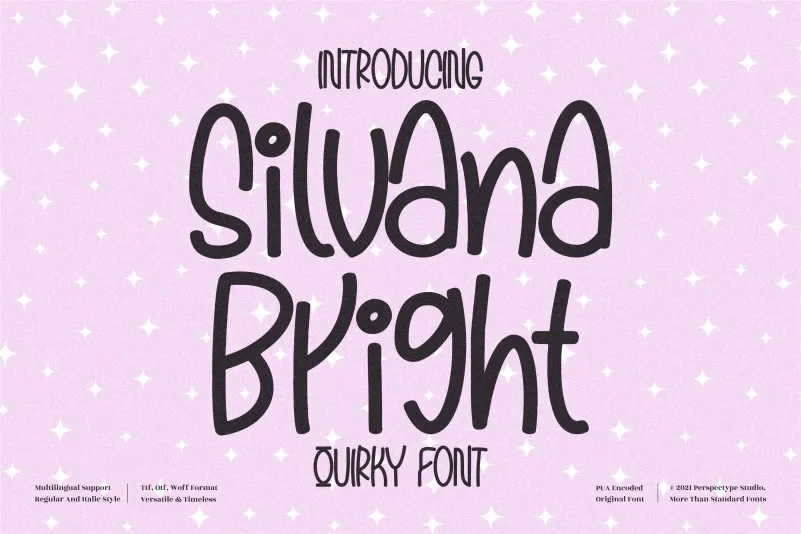
A fonte “Silvana Bright” é uma escolha perfeita para aqueles que desejam adicionar uma pitada divertida às suas criações digitais. Esta fonte escrita a mão tem um toque descontraído e original, o que a torna especialmente interessante para designers de todos os níveis. Ela se destaca em qualquer projeto e é perfeita para aqueles que buscam um tom criativo e único. Seja você um estudioso da arte gráfica ou simplesmente alguém que aprecia design visual, “Silvana Bright” oferece uma maneira divertida de transformar suas ideias em realidade, fazendo-as parecer ainda mais vivas e inspiradoras. Adicione essa fonte ao seu catálogo de recursos, e você notará como ela realmente torna seus projetos únicos e atraentes.